Akkolade
In der Typografie ist eine Akkolade eine geschweifte Parenthese; geschweifte Klammer; umgangssprachlich auch als »Nasenklammer« bezeichnet. Plural Akkoladen. Etymologisch aus dem Französischem »accolade« für »Umarmung« aus dem Lateinischen »ad« für »zu« und »collum« für »Hals«. Satzzeichen, welches Noten-, Code- und Textzeilen zusammenfügt.
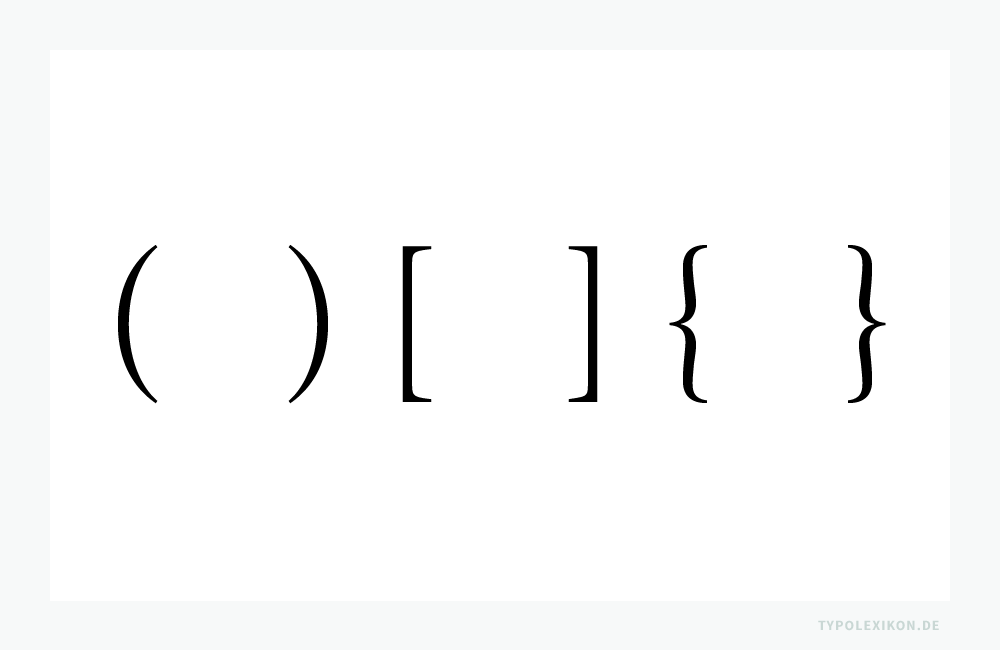
Für die formale Anwendung von Akkoladen in der Textgestaltung gibt es keine verbindlichen Vorschriften. 1) Sie finden im deutschsprachigen Raum, abgesehen von wissenschaftlichen und musikalischen Publikationen, kaum Verwendung. 2)
| ↑1 | Anmerkung: Es ist durchaus legitim, innerhalb eines geschlossenen Schriftsatzes Akkoladen anstatt runder oder eckiger Parenthesen zu verwenden. Allerdings sollte dann die Akkolade durchgängig verwendet werden. |
| ↑2 | Tipp: Akkoladen lassen sich in der Gebrauchs- bzw. Akzidenztypografie wunderbar als Schmuckzeichen einsetzen. |